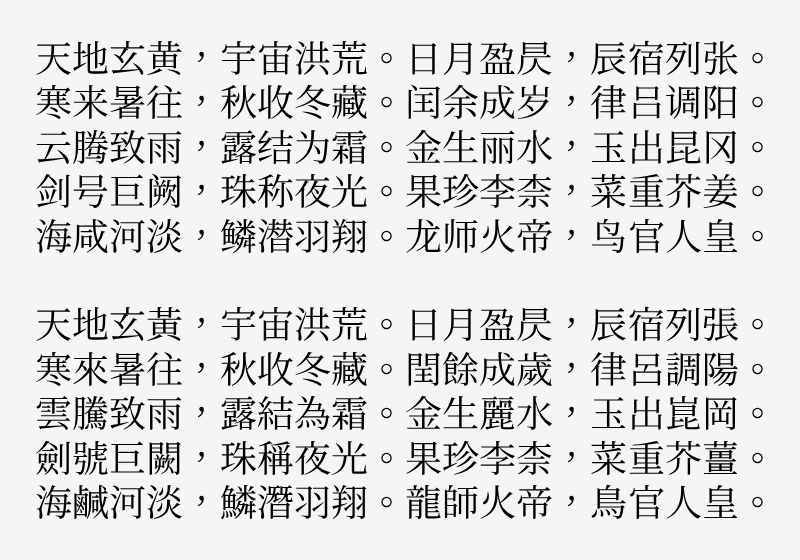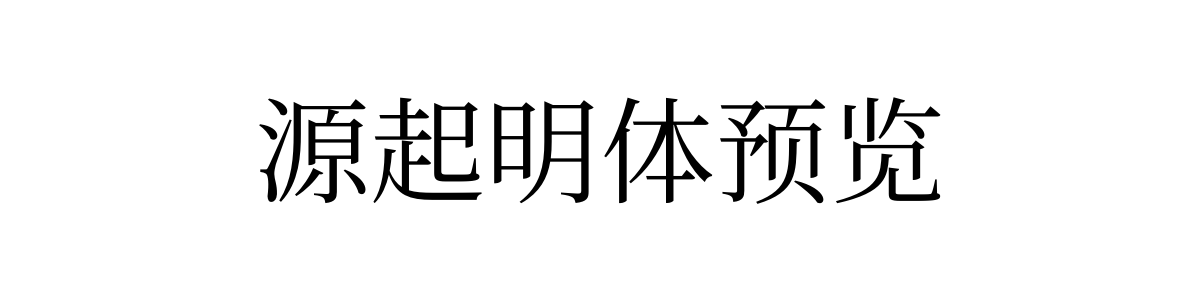
源起明体
源起明体(GenKiMin)是源样明体(GenYoMin)的楷化衍生版本,主要改动是在笔画转折的地方重新做了断笔处理,风格上和原版有明显区别。
沿用了源样明体的 KR 字形结构和置中标点,排版出来整齐又有传统印刷的质感。转折处的楷化处理让字体既清晰易读,又带有书写的流畅感。
字体风格
源起明体的设计上以楷书笔意为核心,将毛笔书写的起承转合融入规整的印刷字体框架,通过细腻的断笔效果和笔形变化,让字体既有宋体的清晰骨架,又有手写般的亲和力。